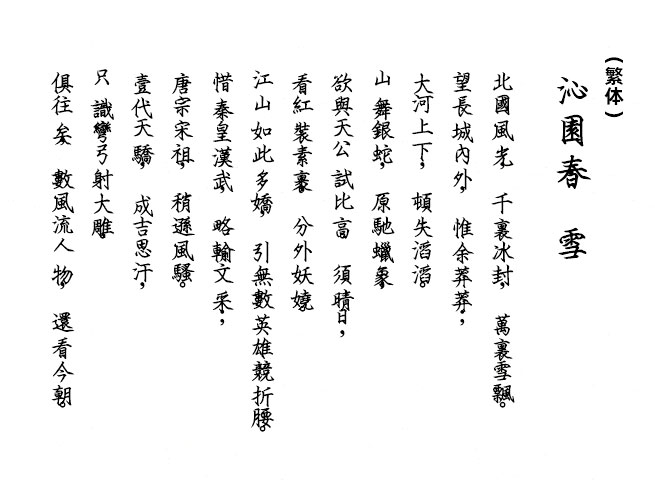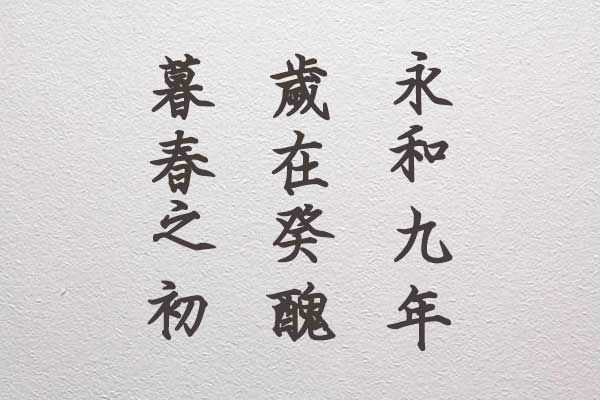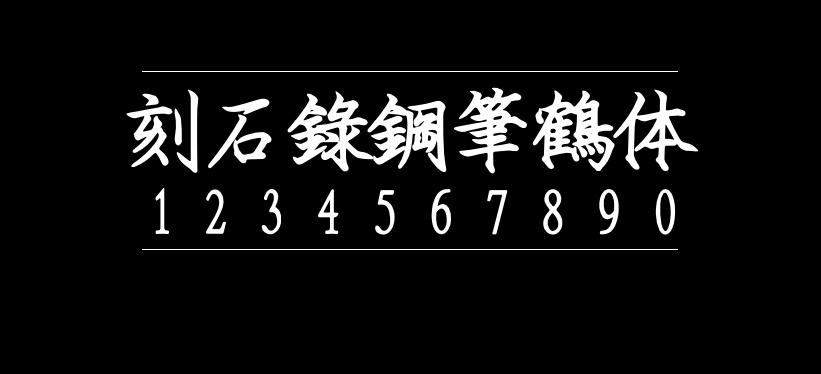
刻石录钢笔鹤体
刻石录钢笔鹤体(I.PenCrane-B 、刻石錄鋼筆鶴體)由王汉宗粗钢体修改而来,刻石录重新制作和修整原字型中缺少的或有欠美观的部份,例如半形英数、圈圈字、常用符号等。刻石录钢笔鹤体是一款非常不错的中文艺术字体,该字体笔画遒劲灵动,连笔张弛有度,结体清丽优美,整体效果很不错,能够适用于艺术设计、包装印刷、签名设计、图形设计等领域。
至于对汉字部份的修改,不外乎两种工作:一、改变字形写法,二、增補缺字。改变字形者,把字型中一些从俗的写法,改为正统的字样。
例如:“青”字下方本从“円”,即“丹”;“聪”字本从“囱”,而非“囱”;“氐”字末笔为横,不是点等。然而,由于鹤体乃由笔写楷书字体发展而来,属手写字型,因此也接受一些手书写法,如“纟”旁下方作三点;“饣”旁也不改作“⻞”等。补字者,则增造常用香港外字表中的字。目前已完成外字表版本1.3里除Ext-B部份(即编码有五位、以“2”字开首的字符)的A至C级、1至5级,和i级字符。 修改以后,在下将之发布作开源字型“I.钢笔鹤体-粗”,好让极度缺乏实际字体的开源字型世界里,补回应当存在的一员。字型名称里的“I”是罗马数字“一”,“I.”唸作“一点(いちてん、One-dot)”,象征笔画的基本:点与线。
刻石录钢笔鹤体